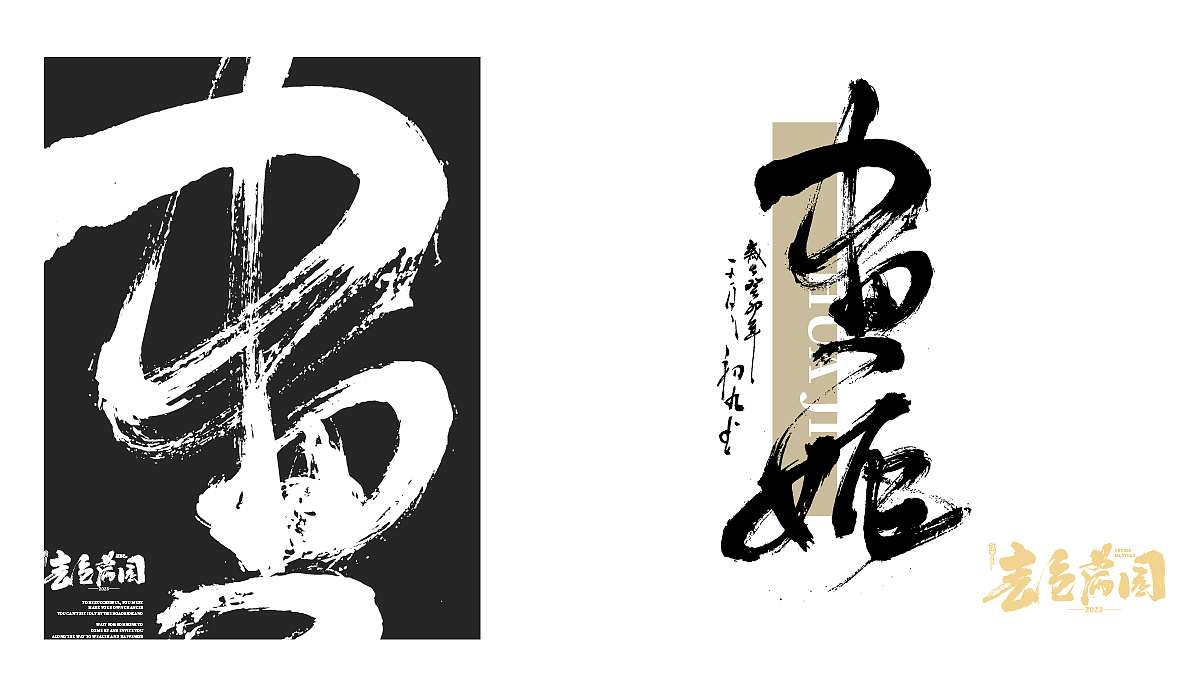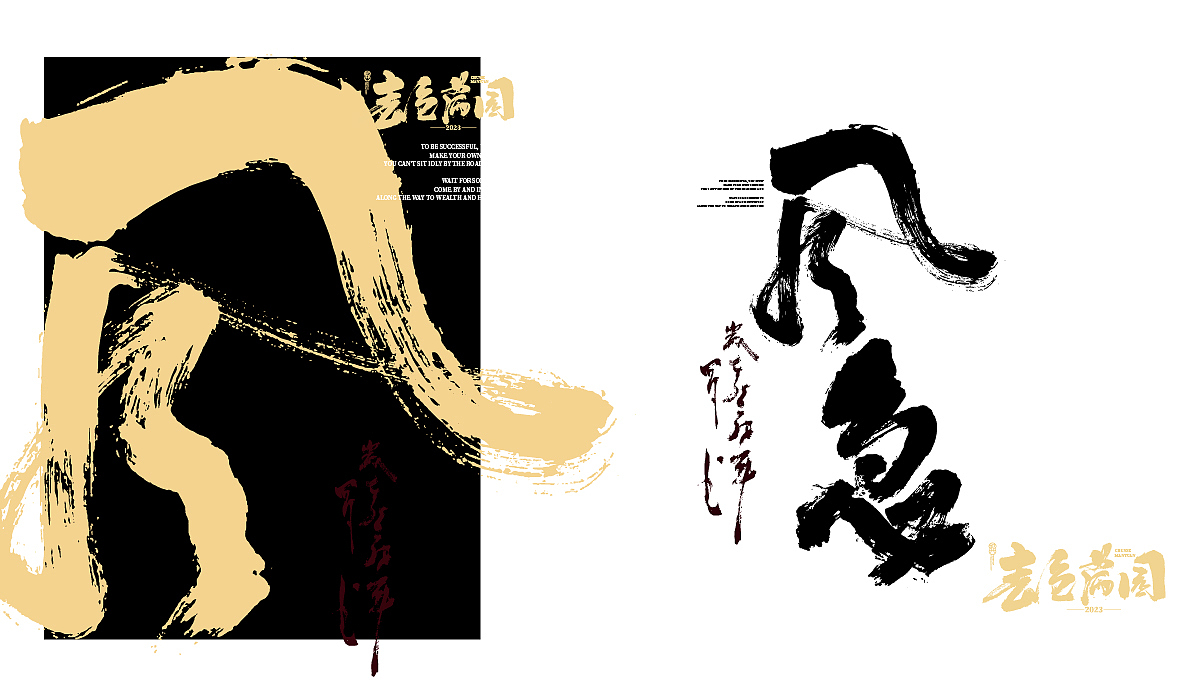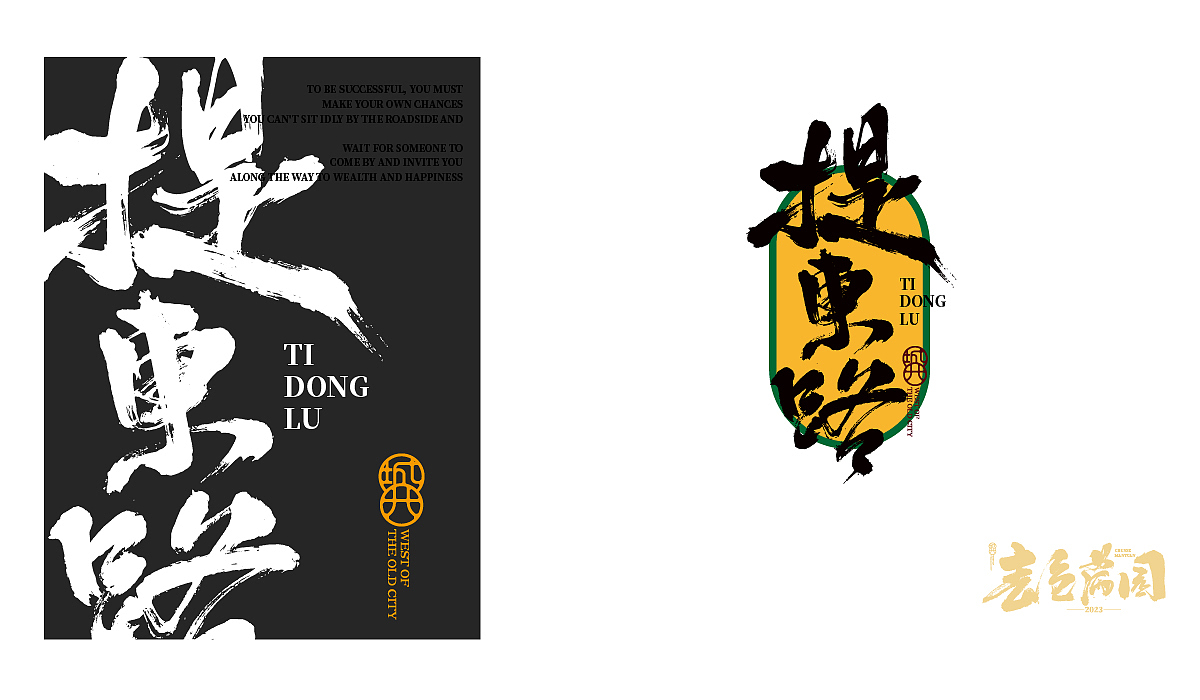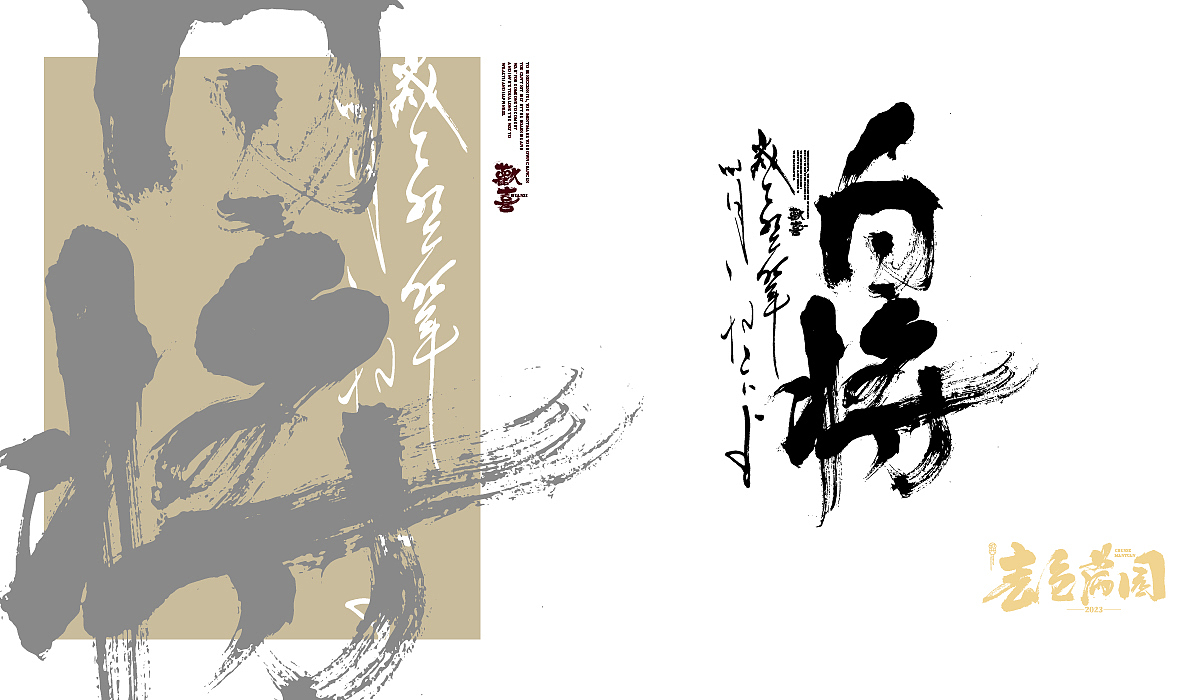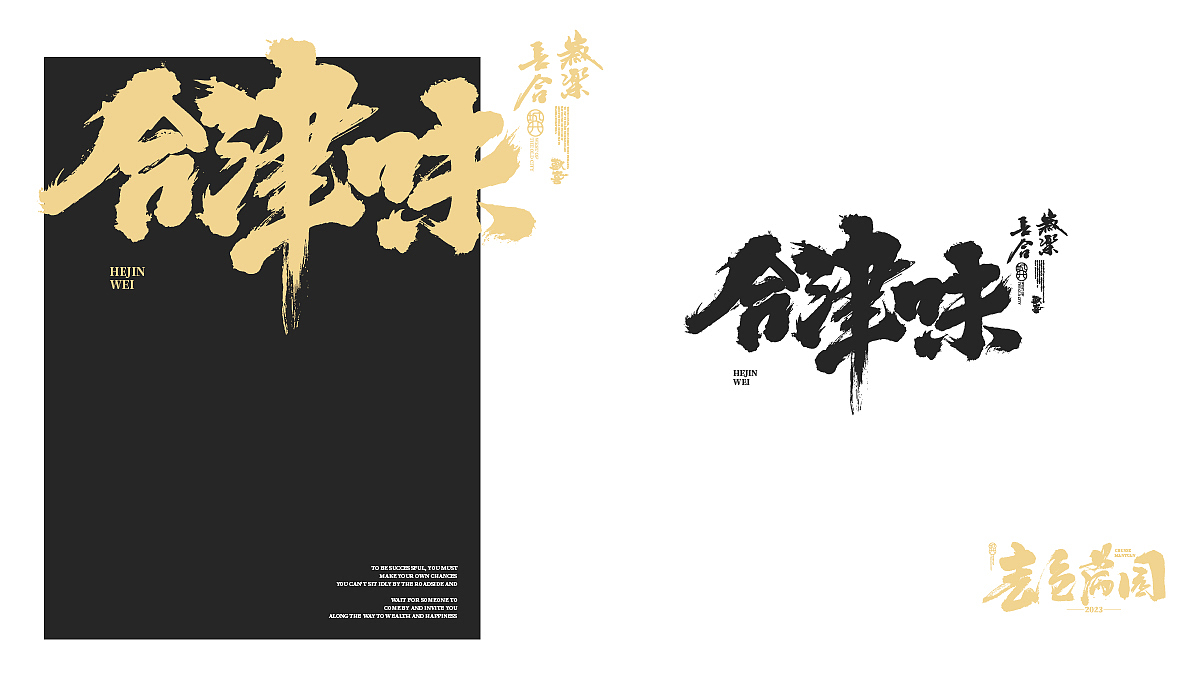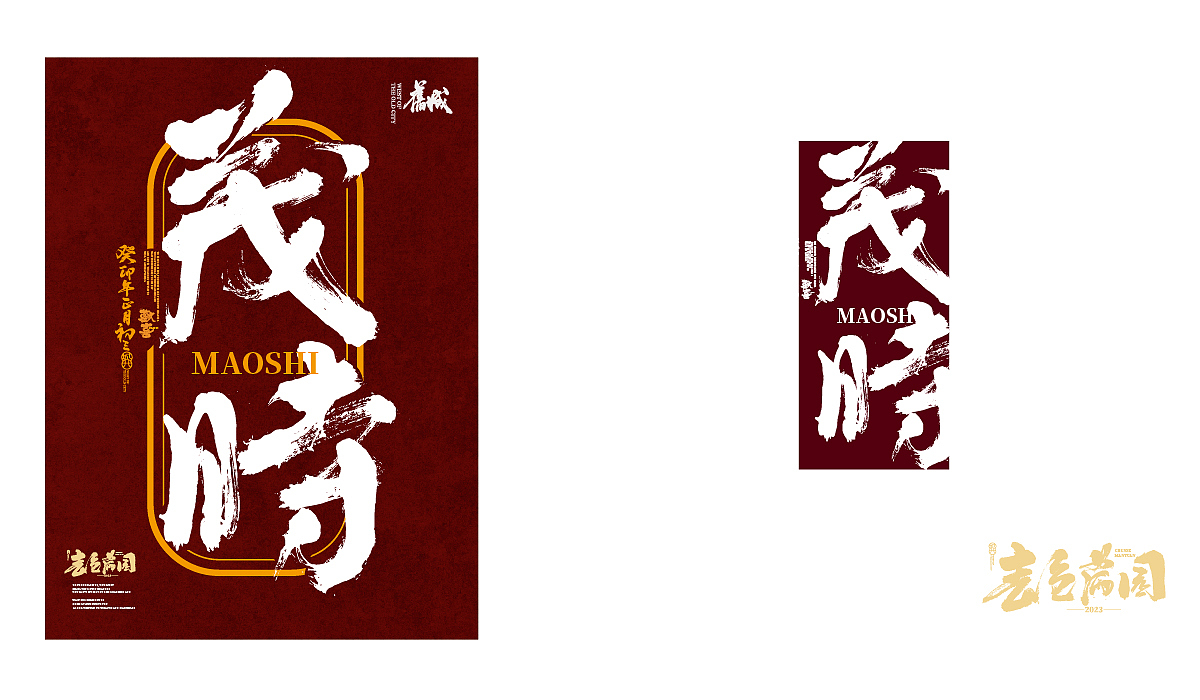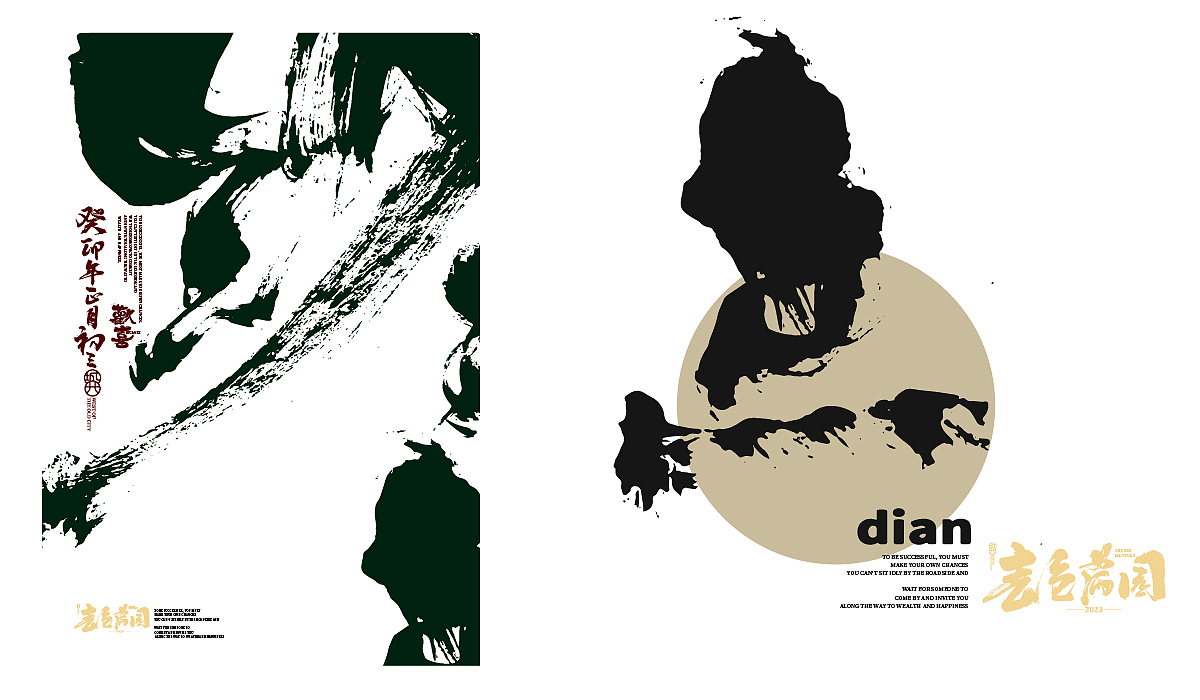
八月手书字型-X-书法字体-X-潮字型
八月整理(手写字体)
这个月更新的字型已经开始往一个方向去了
主打的以大视觉为主——泼墨感
大众的审美倾向已经以笔刷、刺激性的、夸张的方式
我总感觉时间长了会有一种疲劳在内
所以后面有些作品是借鉴了一些古帖的字体结构
反正我自己是觉得很耐看的
主要工具:纸墨笔砚——常规毛笔、半生熟宣纸